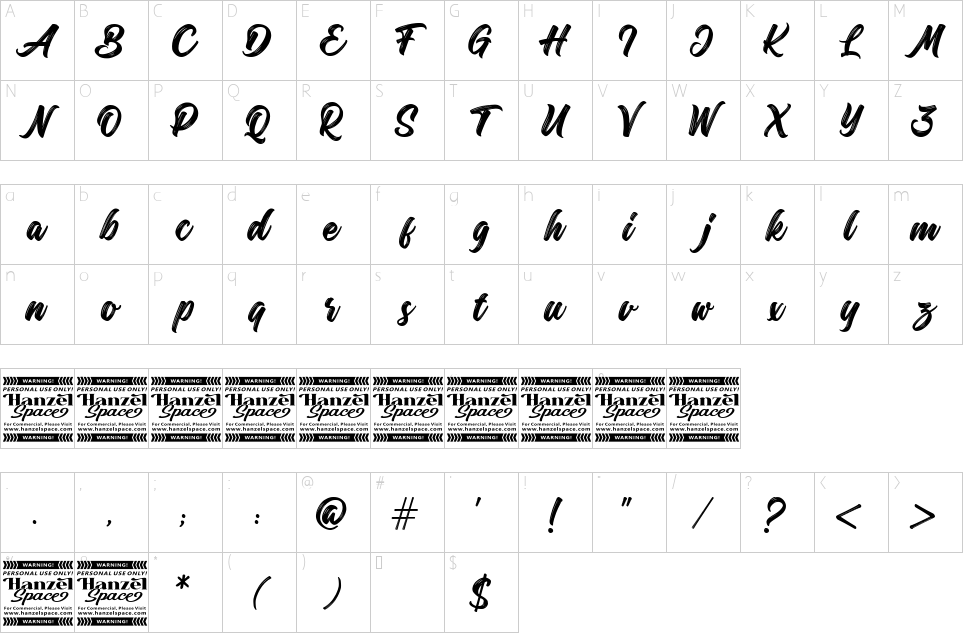
Descubra a essência da designação e criatividade com Margadeth, uma fonte grátis para Windows e Mac. Criada pela Hanzel Space, esta fonte destaca-se com suas linhas elegantes e sofisticadas, adequada para diversas aplicações de design, desde textos de newsletter até gráficos de mídia social. Com 5,140 downloads, é evidente que Margadeth se destaca pelo seu charme único e versatilidade, tornando-se uma escolha ótima para designers que buscam uma fonte de qualidade sem precisar gastar. Descubra Margadeth e transforme seu design em algo de verdade.